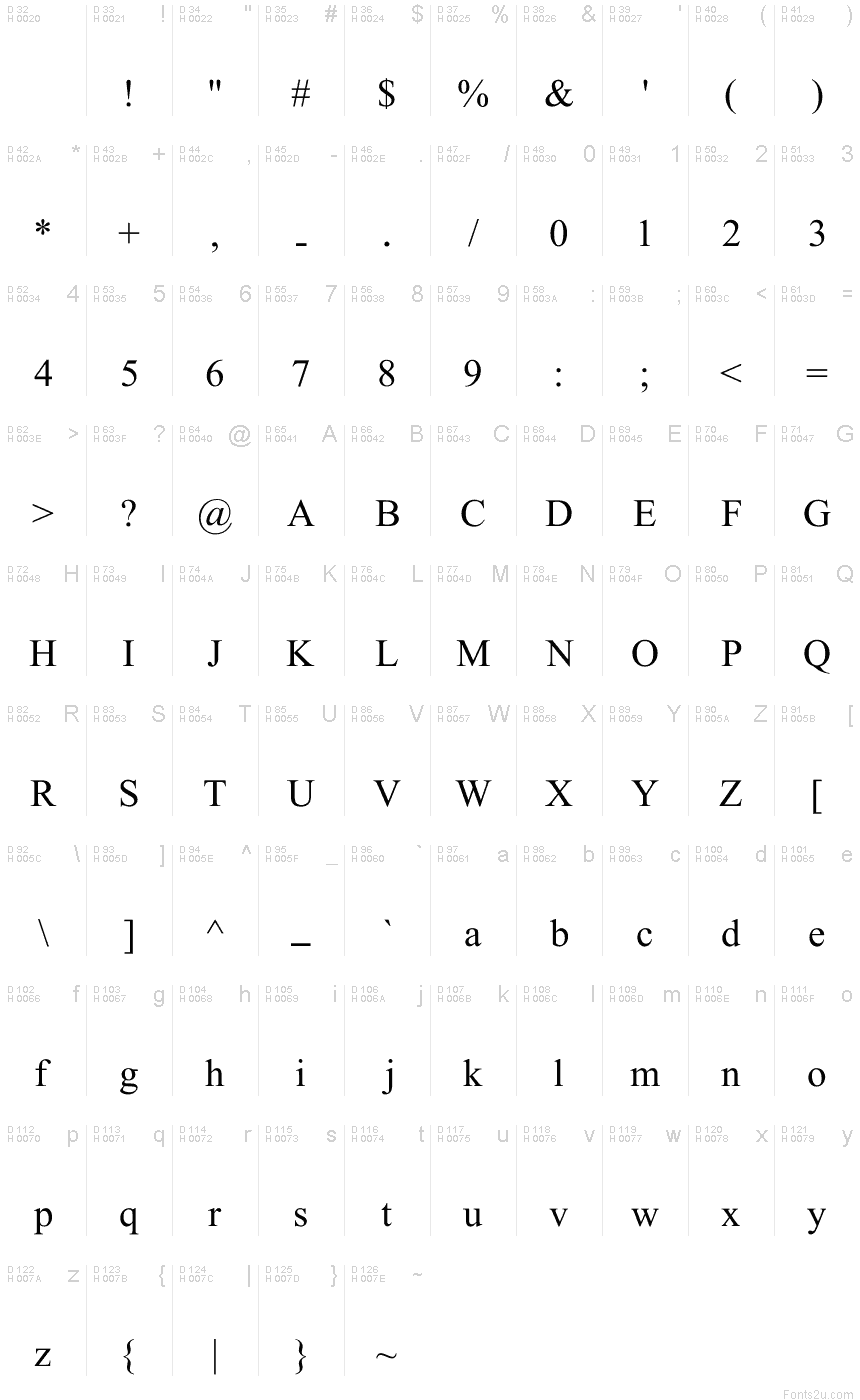
UKIJ Zilwa von der Uyghur Computer Science Association ist eine kostenlose Serifenschrift mit hohem Kontrast und dem formellen Charakter alter Plakatschriften. Die Großbuchstaben setzen auf hohe Vertikalen, feine Haarstriche und scharfe, fast blockartige Serifen. Details wie das geschwungene J und das markant geschnittene Z verleihen den Buchstaben eine fast theatralische Note.
Die Schrift eignet sich hervorragend für Magazinköpfe, Buchtitel, Plakate für kulturelle Veranstaltungen, Titelkarten und Monogramme – überall dort, wo es auf eine gewisse Feierlichkeit statt auf Weichheit ankommt. Als kostenloser Font spielt UKIJ Zilwa seine Stärken besonders bei kurzen Überschriften und Initialen aus, da die starken Kontraste und die prägnanten Großbuchstaben auch ohne viel Text für eine beeindruckende Präsenz sorgen.